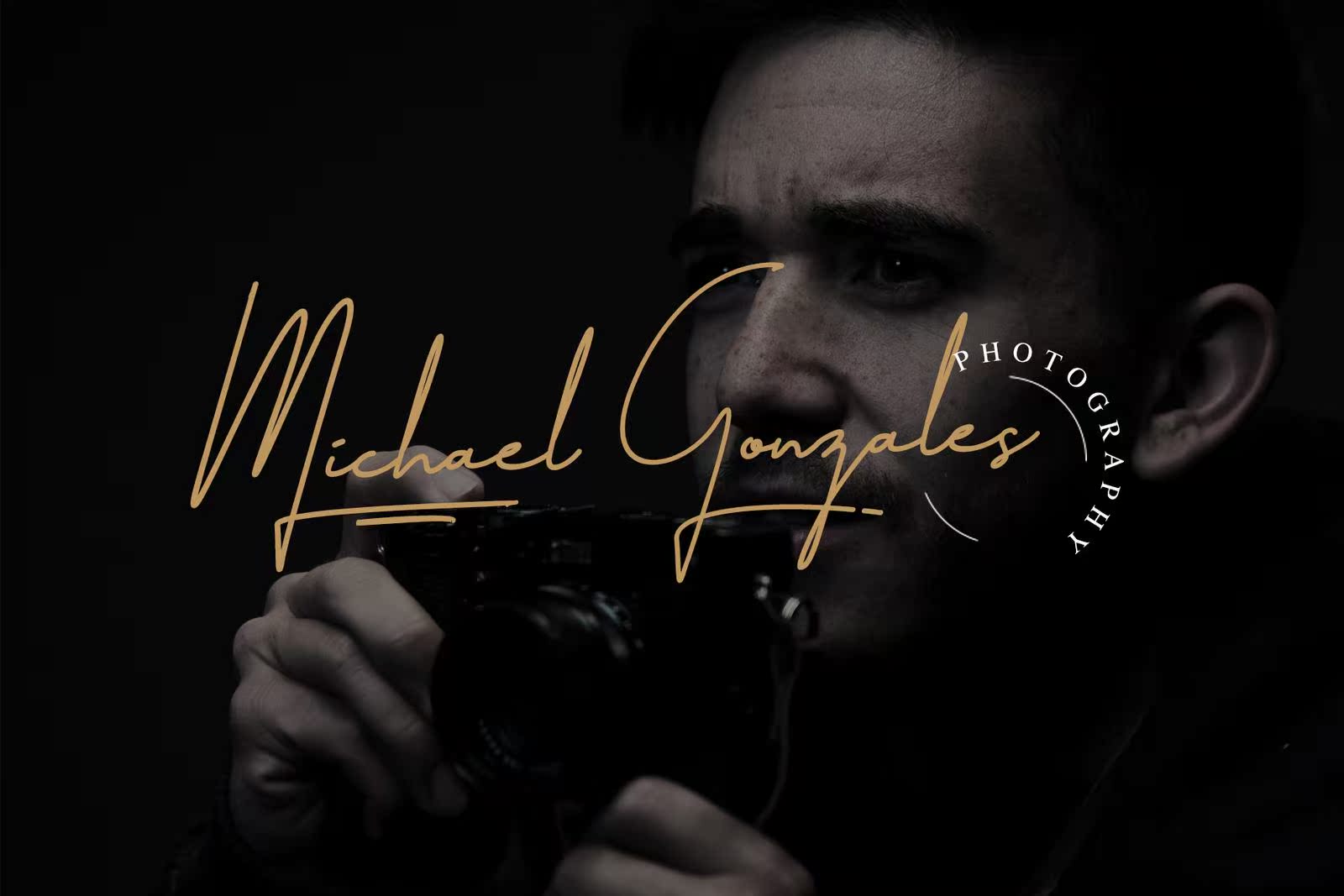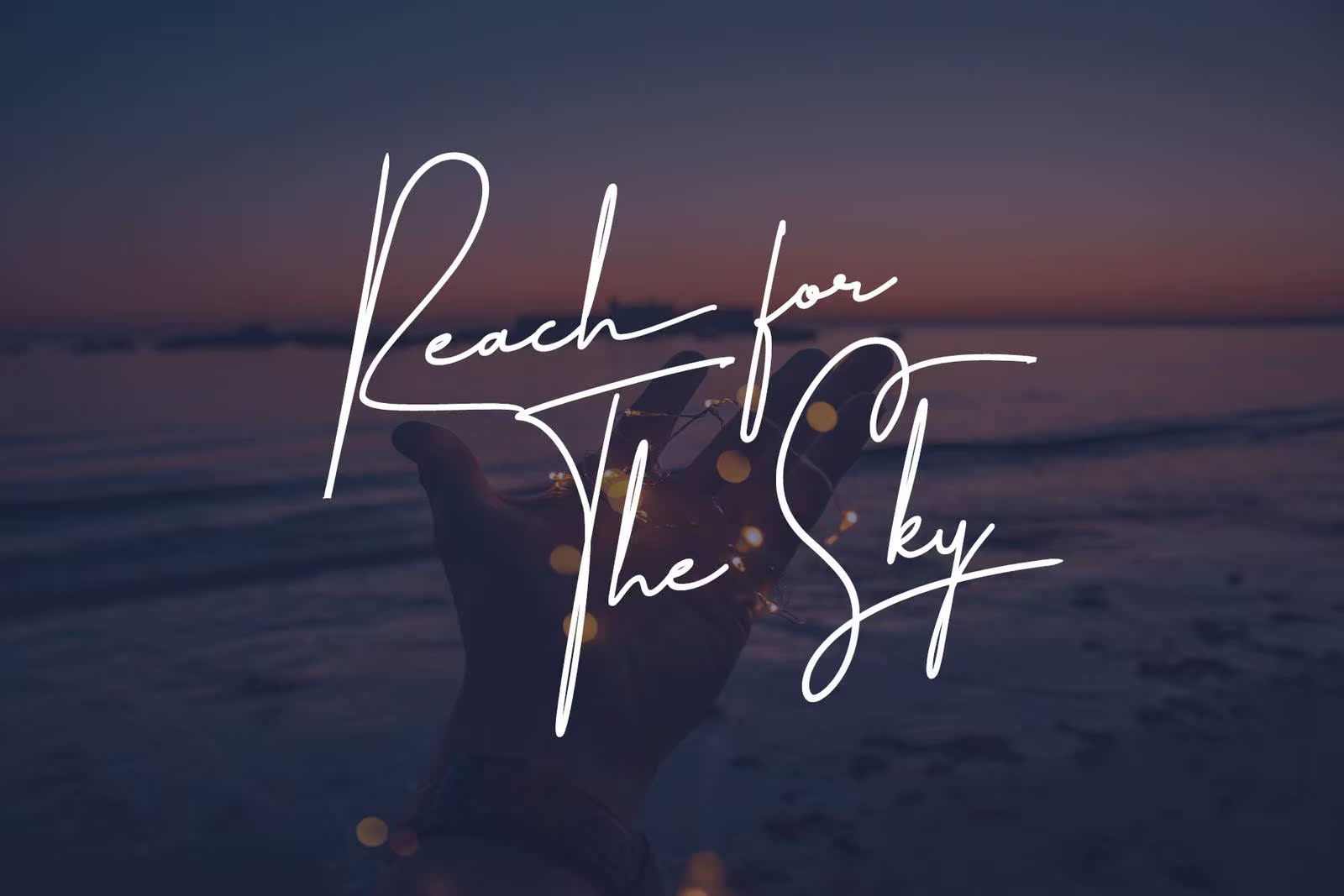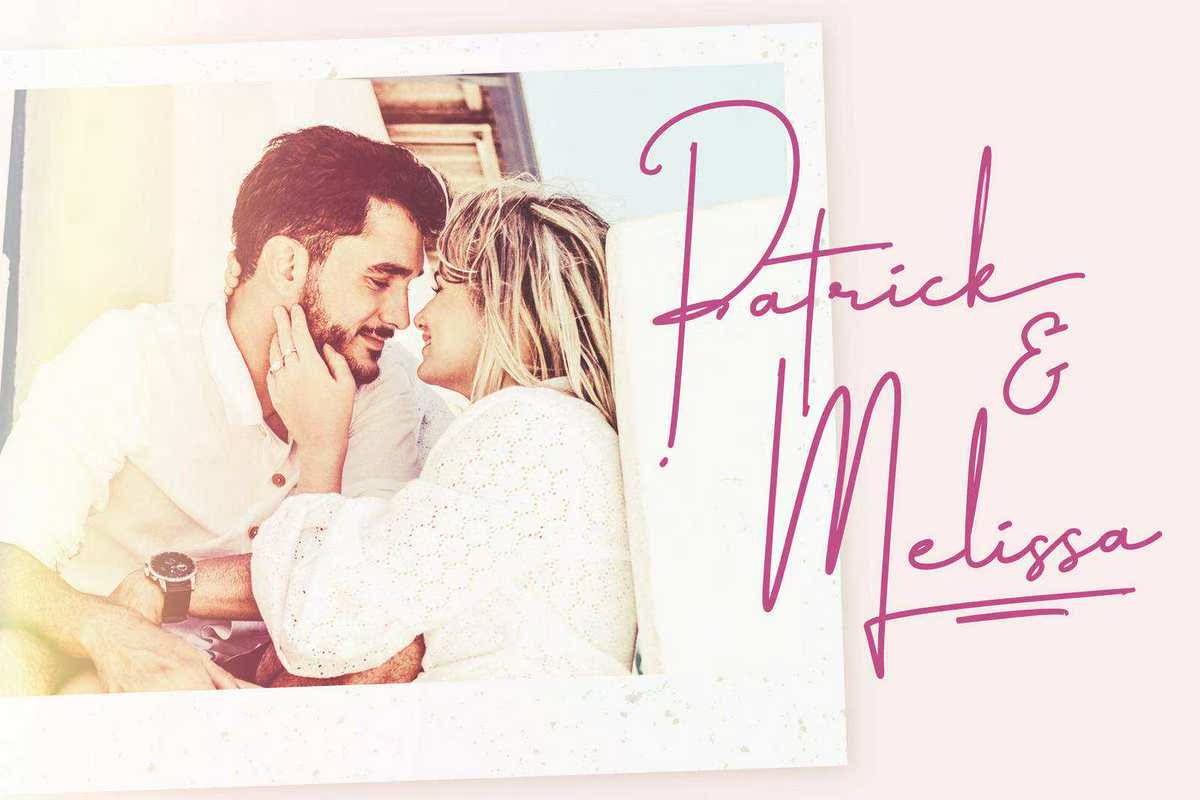
AmilliaSignature是一种具有细线和自然风格的手工签名。由于其独特的特点,AmilliaSignature字体适用于徽标、社交媒体、广告、产品包装、产品设计、标签、摄影、水印、邀请、,文具商和其他任何需要使用简洁样式字体或简单文本覆盖在任何背景图像或引用图像上的项目。AmilliaSignature是一种具有细线和自然风格的手工签名。由于其独特的特点,AmilliaSignature字体适用于徽标、社交媒体、广告、产品包装、产品设计、标签、,照片、水印、邀请函、文具和其他任何需要AbrushStyleFontor的项目,或者简单地在任何背景图像或QuoteImages上覆盖Astylish文本。